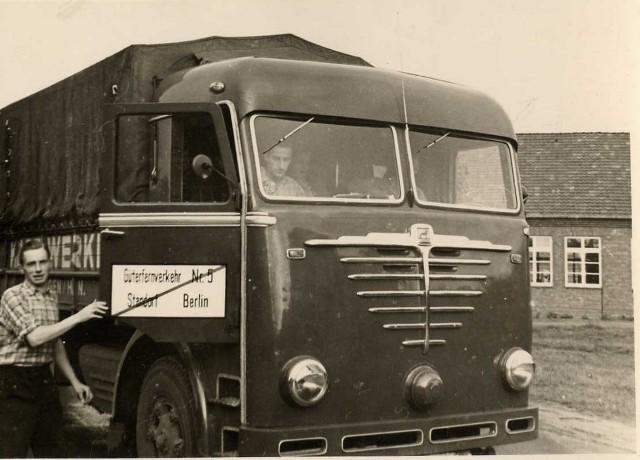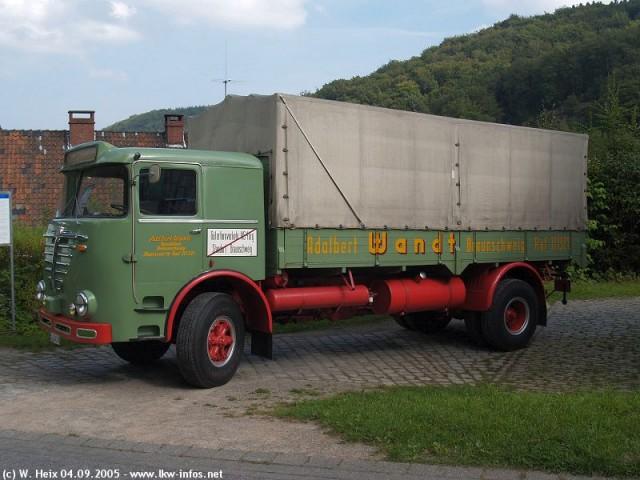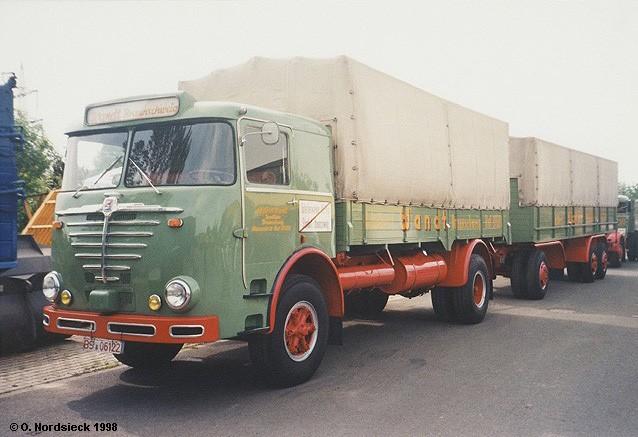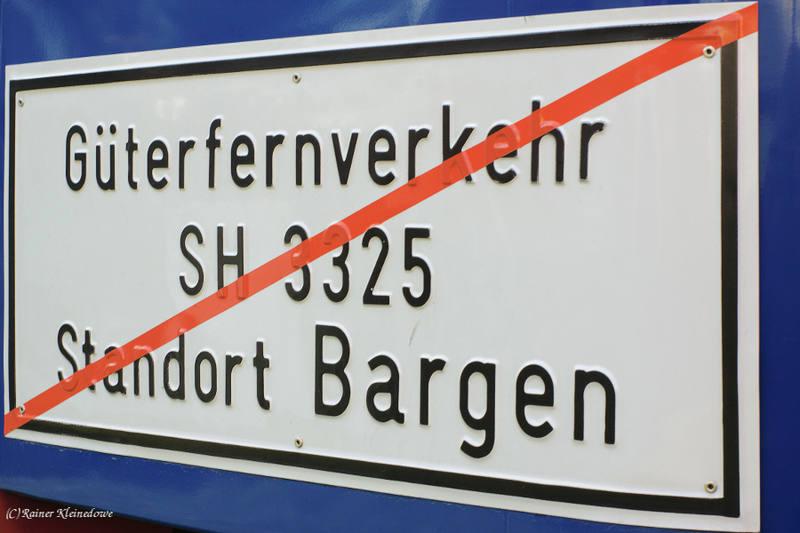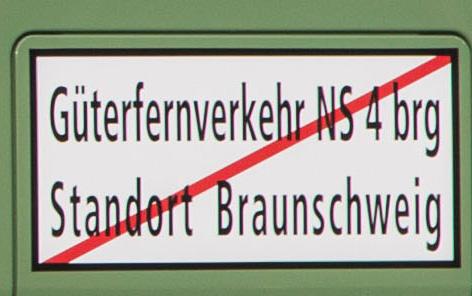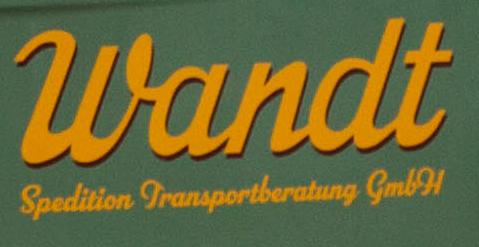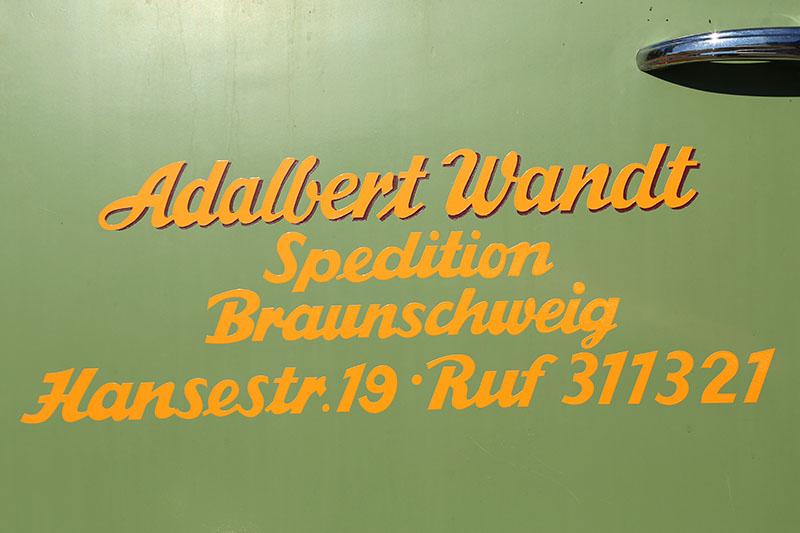
LKW-Beschriftung 1930er Jahre?
Eine Spedition bei uns beschriftet zum 80jährigen Bestehen einen LKW mit historischem Schriftzug, vermutlich so wie er damals beschriftet worden wäre.
An der der Sonnenblende über der Windschutzcheibe  steht die Zahl des Gründungsjahres 1939. Ich weiß nicht, ob das Ausehen der Zahl identisch zu der verwendeten Schriftart ist. Das dritte Bild zeigt die Bechriftung eines Oldtimers aus der 1960er Jahren, die wohl identisch zu dem neuen Fahrzeug  ist. Könnte es sich bei dem Vierten Bild "Güterfernverkehr" um DIN 1451 handeln?
Ich würde das Fahrzeug gerne als Modell nachbauen und habe auch schon viele Schriften durchsucht, aber irgendwie noch nicht das passende gefunden. Kann mir veilleicht hier jemand helfen?
"Güterfernverkehr" ist eher eine auf 50 % Breite gequetschte Frutiger Condensed.
Ja, ich kann mich noch an diese Schilder erinnern, das war eher nicht aufgemalt, sonder geprägte Alu-Blechschilder, und daher auch in DIN 1451, genau wie damalige Nummernschilder geprägt.
Die restlichen Beschriftungen waren keine Satzschriften sondern wurden nach einer einmal von einem Schildermaler erstellten Reinzeichnung zunächst mit einem Storchenschnabel auf Zeichenpapier in der gewünschten Größe übertragen.
Dann wurde eine Stanniolfolie mit Zuckerwasser auf das lackierte Autoblech geklebt, darauf mit Malerkrepp sie passend skalierte Papierzeichnung der Beschriftung befestigt, und diese mit einem Pausgriffel (Ein Stift, der am Ende einen Stahlstift hat, der mit einer etwa 1mm Kugel endet) wird die Zeichnung auf die Zinnfolie durchgedrückt.
Anschließend wurde die Zeichnung entfernt, und die zu lackierenden Flächen der Zeichnung mit einem Federmesser aus der Zinnfolie herausgeschnitten. Verbliebener Zucker auf fiesen freigelegten Flächen lässt sich leich mit Wasser abspülen, dann wurde Lackiert, die restliche Zinnabdeckung entfernt. wird eine weitere Farbe gebraucht, geht das ganze von vorn los. Ich habe in meiner Lehre noch miterlebt, wie KFZ-Lackierer dies lernen mussten.
Weil hier bei der Neulackierung dieses sonst immer als Blechschild gefertigte Schild offensichtich vom Original abweichend aus einer gequetschten Frutiger in Folie geschnitten wurde
So seh ich das auch, ja.
Ein Original sieht so aus – ist aber auch keine DIN 1451.
Aber eben die Standsrd-Prägeschrift, welche damals von den Schilder-Prägemaschimen-Herstellern geliefert wurde. Auch das waren keine Satzschriften, sobdern eben speziell für diesen Zweck entworfen, irgendwie schon von der DIN-Schrift inspiriert.
Das sag ich ja. Zwischen „das ist die DIN 1451“ und „das ist von der DIN inspiriert“ ist aber ein großer Unterschied, und daher kann man die Frage „Könnte es sich bei dem Vierten Bild »Güterfernverkehr« um DIN 1451 handeln?“ nur mit „Nein“ beantworten.
So kategorisch würde ich dies auch nicht sehen, schließlich wurden diese Schilder von den örtlichen Schilderherstellern geprägt, und da werden eben auch viele die DIN 1451 verwendet haben, die möglicherweise für diese Schilder sogar im Gesetz stand, andere, die dann sonst Schilder fertigten, wie "Spielen auf dem Trockenplatz verboten" oder "Vertreter unerwünscht" verwendeten eben die Schrift, welche sie zur Verfügung hatten, das hat man wohl hier nicht so eng gesehen.
Möglicherweise ist aber das gezeigte Schild auch eine nicht richtig präzise Nachfertigung aus jüngerer Zeit, darauf weist das rote Isolierband über die Schrift hin. Im Original war der rote Querstrich schon auf das noch ungeprägte Blech lackiert, und in meiner Erinnerung auch etwas breiter, sodass die schwarze Schrift dann über dem roten Diagonalbalken stand. Solche Original-Rohlinge stehen heute wohl nicht mehr zur Verfügung, so hilft man sich bei Fahrzeugrenovierungen eben mit einigermaßen in der Größe passenden Rohlingen für Hinweisschilder und auch mit einer möglichst ähnlichen Schrift, deren unterschied der Mehrheit der Betrachter wohl kaum auffällt.
Ich würde hier eindeutig nein sagen. wenn man sich mal die 1 und 3 für die Telefonnummer und der Jahreszahl anschaut ist da ein Unterschied erkennbar.
Wenn es aber so am Originalfahrzeug beschriftet wurde, würde ich es auch so lassen. Bei Restaration sollte der Originalzustand erhalten beiben.
Die Schrift für das Schild "Güterfernverkehr" scheint aber auch nicht genormt worden sein.
Eine gequetschte Frutiger Condensed zu verwenden, ist auf jeden Fall verkehrt, da sie erst weit nach Inkrafttreten des Güterkraftverkehrsgesetzes und der Prägung entsprechender Schilder gestaltet wurde.
Nun hab ich das mit der 1939 verstanden. Die schrift, wie oben schon geschrieben ist sichtbar eine andere.